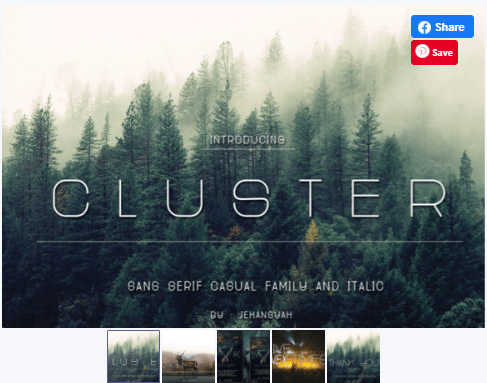
Cluster Font
Cluster - элегантный и приятный шрифт без засечек. Он идеально подходит для тех из вас, кто ищет спокойствия в выражении идей с помощью большого заголовка, и этот шрифт идеально подходит для размещения где угодно, особенно если вы используете его в качестве заголовка или в официальном письме.